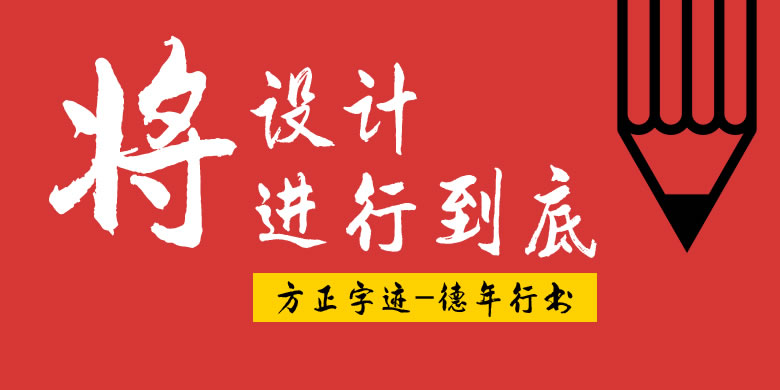
品牌:方正字迹设计师:金德年发行时间:2014字库编码:大陆简体(GB2312-80)、大陆繁体(GB12345-90)、简繁扩展(GBK)分类:常规书写·毛笔
方正字迹-德年行书的书写功力圆熟,用笔刚健爽快,笔力遒劲,笔画浑厚宽阔,洋溢着当代书写美感。这款字体的风格热情奔放,适用于文化类的宣传设计,以及商业类品牌的广告和产品包装设计。